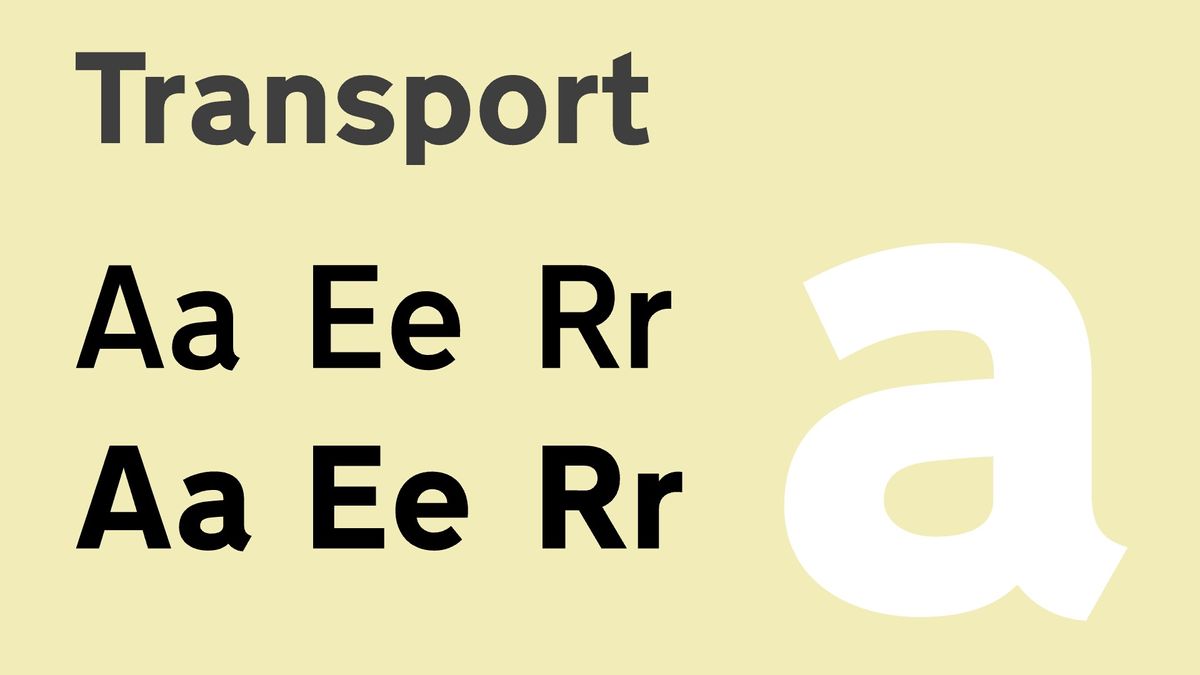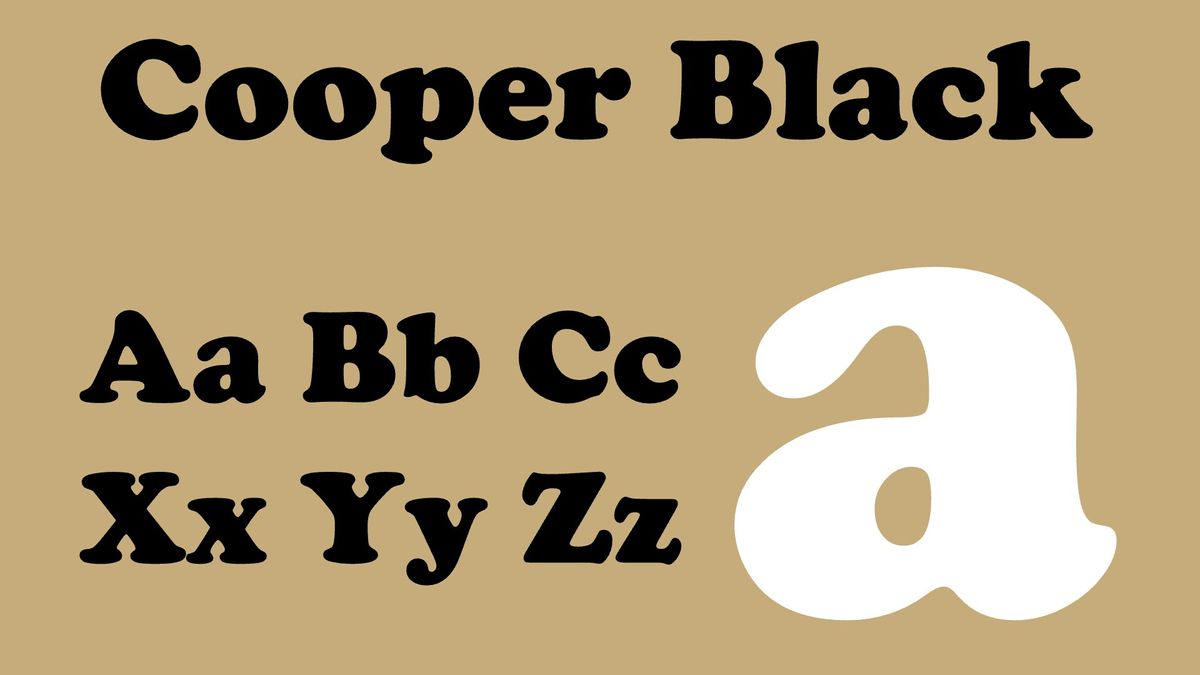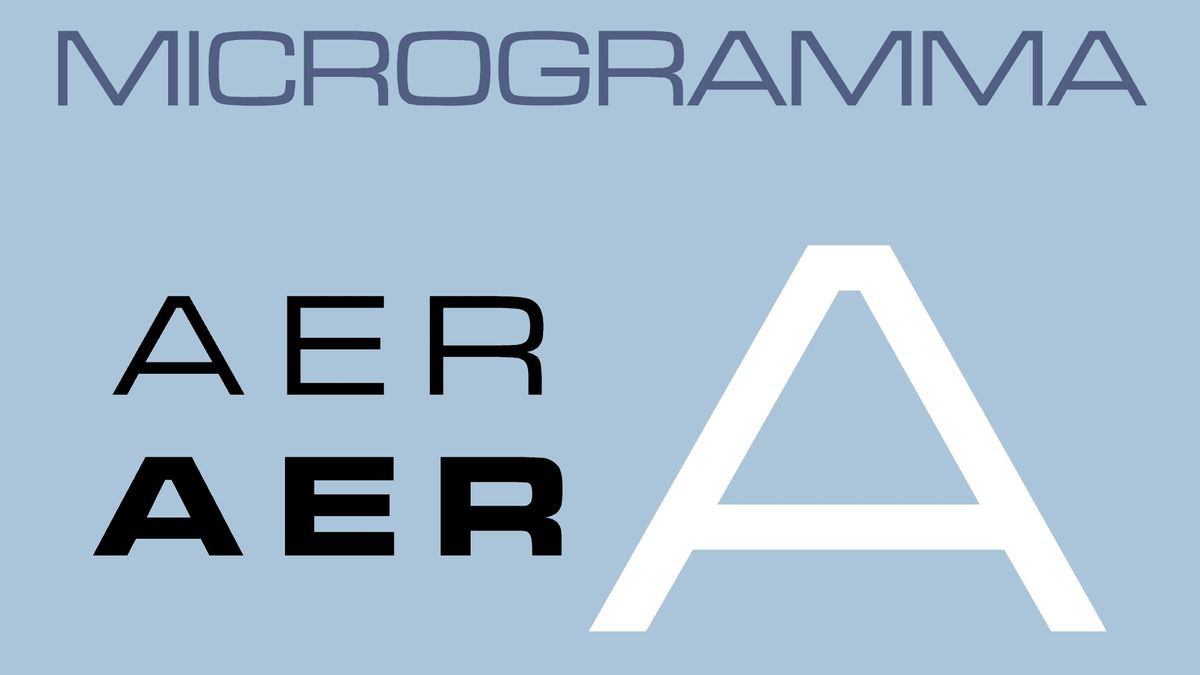
Введение: Отпечаток эпохи
Эй, ребята! Давайте немного пофантазируем о том, как выглядел мир в 1950-х. Время, когда все вдруг вдохнули в себя воздух свободы, когда начали меняться не только привычки, но и сам язык визуальной коммуникации. 📜 Типография в этот период стала настоящим отражением общественных трендов, и, поверьте, это не просто красивые буквы на бумаге. Это глубинный процесс, охватывающий всевозможные аспекты культуры и бизнеса.
В этой статье мы не просто пробежим по шрифтам 1950-х. Мы заглянем за кулисы и увидим, как именно эти формы и линии формировали понимание брендов и визуальной идентичности. Готовы? Погнали!
Буквы, которые изменили всё
Итак, начнем с основ. Когда мы говорим о шрифтах 50-х, на ум приходит сразу пара ярких имен. Кому-то из нас могут показаться знакомыми шрифты, такие как Helvetica или Courier. Но что они на самом деле значат для дизайна и брендинга? Давайте расставим акценты.
1. Courier – друг сценаристов и не только
Моноширинный шрифт Courier вскоре стал символом экранного письма. Представьте себя в роли начинающего сценариста, стучащего по клавиатуре пишущей машинки. 🙌 Привет, вдохновение! Его простота и лаконичность считаются чуть ли не величайшим подарком для всех творческих людей — от писателей до дизайнеров. Неудивительно, что Courier так полюбился, ведь он точно передает каждую идею без излишней помпезности.
2. Transport и читаемость на ходу
Следующий на очереди – Transport. Созданный для улучшения читаемости дорожных знаков, этот шрифт имеет уникальные формы, которые позволяют быстро считывать информации даже с летящей машины. Какое потрясающее сочетание функциональности и эстетики, да?
3. Vendôme – стиль и изящество
Теперь давайте немного пофантазируем с Vendôme. 🤩 Этот шрифт сочетает в себе традиционные элементы и современные штрихи. Вы легко заметите его на рекламных вывесках или театральных афишах. Он словно дружелюбный шепот, который говорит: "Эй, посмотри на меня, я здесь, чтобы впечатлить!".
4. Akzidenz-Grotesk и его последователи
И как же обойти стороной Akzidenz-Grotesk? Это имя можно встретить в самых разных дизайнах, оно стало основой для многих новых стильных шрифтов, включая легендарную Helvetica. О, да, эта шрифт — универсальный солдат типографии! По сути, он создал своего рода революцию, заставив дизайнеров задуматься об эстетике и функциональности в одном флаконе.
5. Helvetica – ЭТАЛОН шрифта
Helvetica – это помимо всего прочего, шрифт, который был и остается в центре многих брендовых идентичностей. Он стал синонимом четкости и чистоты — как раз то, что нужно для акцента на сути! Каждый раз, когда вы видите этот шрифт, вам не кажется, что он прошел достойный путь от создания до величайших логотипов? А представьте, каково это создавать дизайн, который потом узнают миллионы!
6. Cooper Black – смелый и выразительный
Следующий в нашем списке — Cooper Black. Это шрифт, который как бы закричал: "Я здесь!" Сплошь красный для билбордов и реклама с такими заголовками, что остановить взгляда невозможно. Неудивительно, что он стал предпочитаемым средством для привлечения внимания.
7. Microgramma – будущее в геометрии
Microgramma — это шрифт, который перекликался с футуризмом! Геометрические формы, которые он носил, рисовали перед нами картину технологического прогресса. Честно, разве не захватывающе рассчитывать, что и в дизайне тоже сделано множество шагов вперед?
8. Креативная индивидуальность Сола Басса
И в конце концов, личности тоже играли свою роль! Мы не можем забыть про Солу Басса — настоящую легенду, который использовал типографику, чтобы сделать титры в кино более динамичными и выразительными. 🎬 Это не просто буквы — это эмоции и атмосфера, которую он создавал.
В заключение: Письмо с сердцем
Таким образом, 1950-е годы стали поистине эпохой расцвета типографии, когда каждая буква, каждый шрифт начали нести в себе не просто смысл, а еще и эмоциональный контекст. В этой эволюции можно увидеть, как меняется не только искренность, но и наше восприятие брендов и культуры в целом.